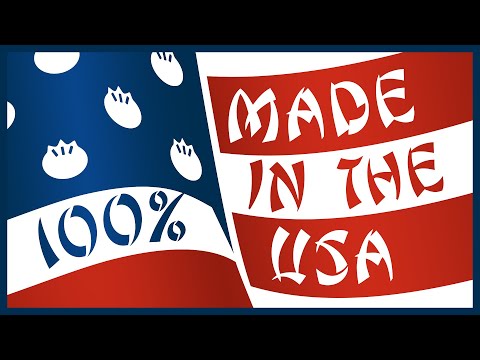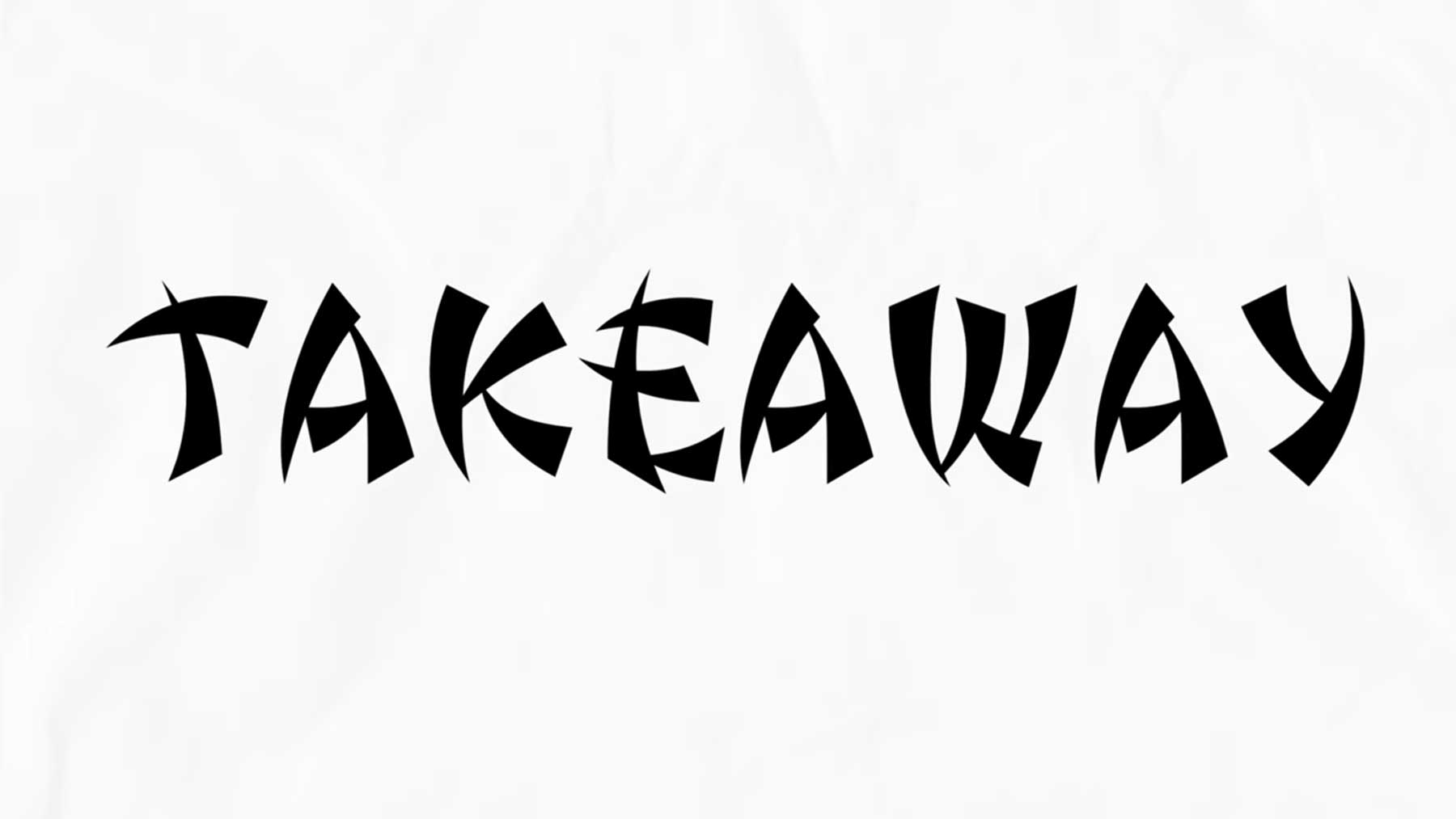
Von Vorurteilen und Gewöhnungseffekten
Geschichte der „Chop Suey“-Schriftart
Vermutlich habt ihr alle schon einmal irgendwie eine Schriftart wie die obige gesehen. Vermutlich beim Takeaway-Essen des fernöstlichen Restaurants im Ort. Tatsächlich hat diese als „Chop Suey Font“ betitelte Art von Schriftarten wenig bis gar nichts mit der eigentlichen Geschichte Chinas zu tun. Entsprechend heikel wird es, wenn man sich das mal genauer anschaut, was Designer Linus Boman für uns gemacht und aufbereitet hat. Der hat uns vorher bereits gekonnt die Geschichte des Swooshes in Markenlogos oder die Entwicklung der olympischen Piktogramme erklärt. Immer wieder lehrreich!
„Chop suey fonts are a subcategory of so-called ‚ethnic‘ display fonts, and are a unique American invention with roots in the 170 year history of Chinese migrants in United States.“